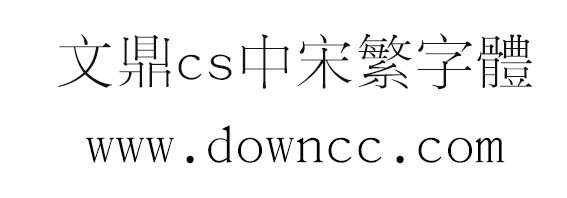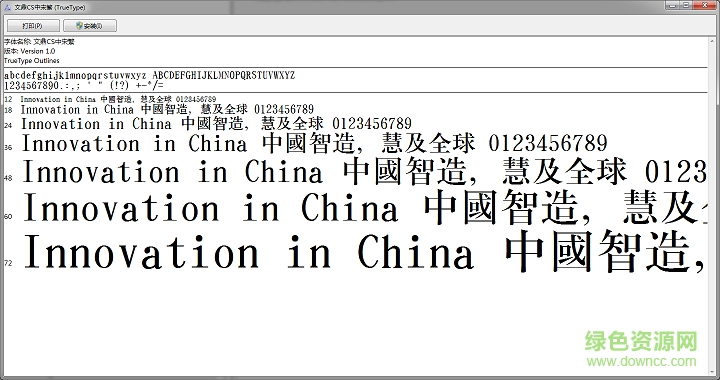
文鼎cs中宋繁是一款筆畫(huà)中等粗細(xì)的宋體繁體字。該字體最大的特點(diǎn)在于,橫細(xì)豎粗,豎筆畫(huà)略微突出部分。喜歡的朋友,趕快到綠色資源網(wǎng)下載體驗(yàn)吧!
文鼎cs中宋繁給人的感覺(jué)就是纖細(xì),筆畫(huà)橫平豎直,非常的端莊,是我們生活中就可以使用的字體